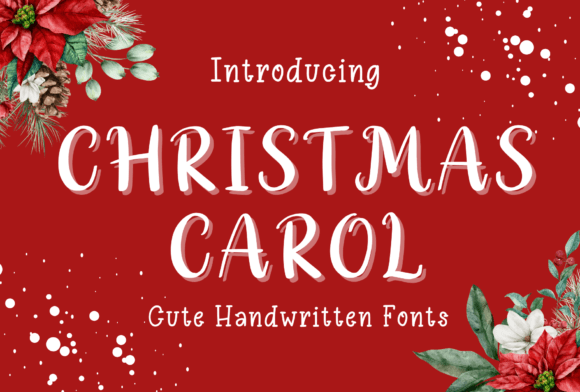
Christmas Carol
การค้นหาองค์ประกอบการออกแบบที่เหมาะสมอาจเป็นเรื่องท้าทาย แต่ Christmas Carol นำเสนอคอลเลกชันที่โดดเด่นซึ่งช่วยยกระดับงานของคุณได้ทันที
ไม่ว่าคุณจะสร้างผลิตภัณฑ์ POD (Print on Demand) คำเชิญงานแต่งงาน หรือกราฟิกโซเชียลมีเดีย Christmas Carol ก็เหมาะสมอย่างยิ่ง